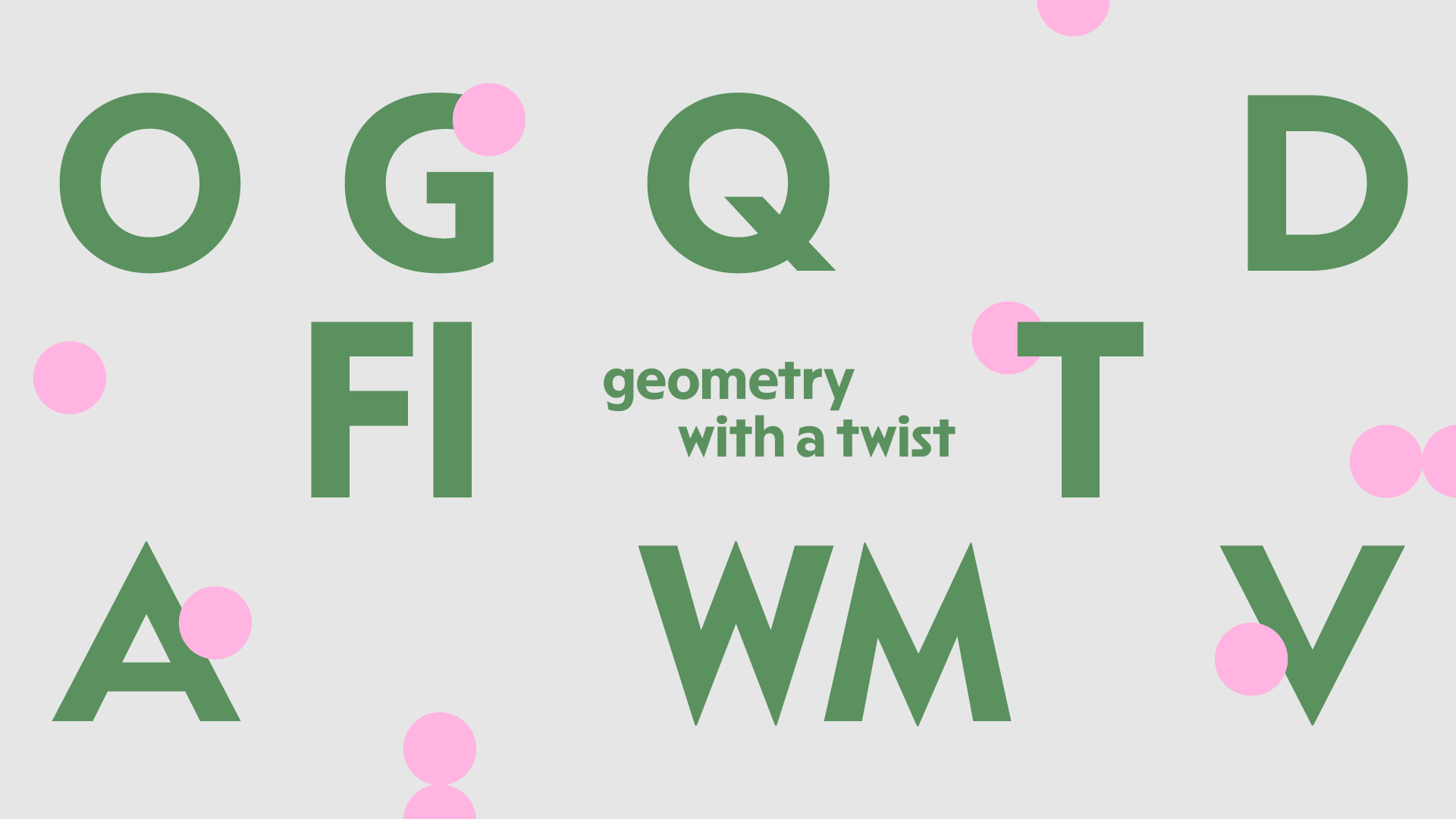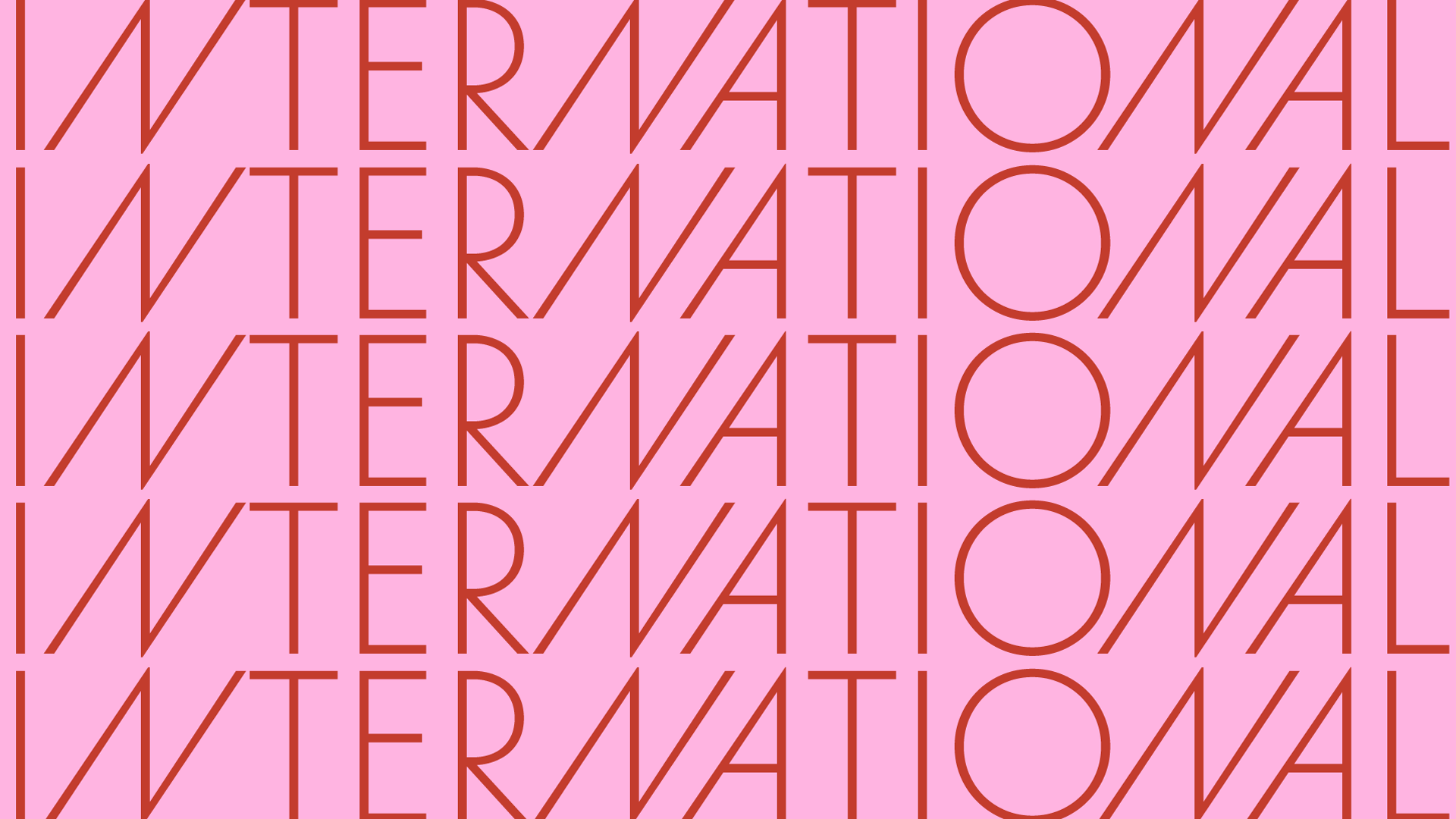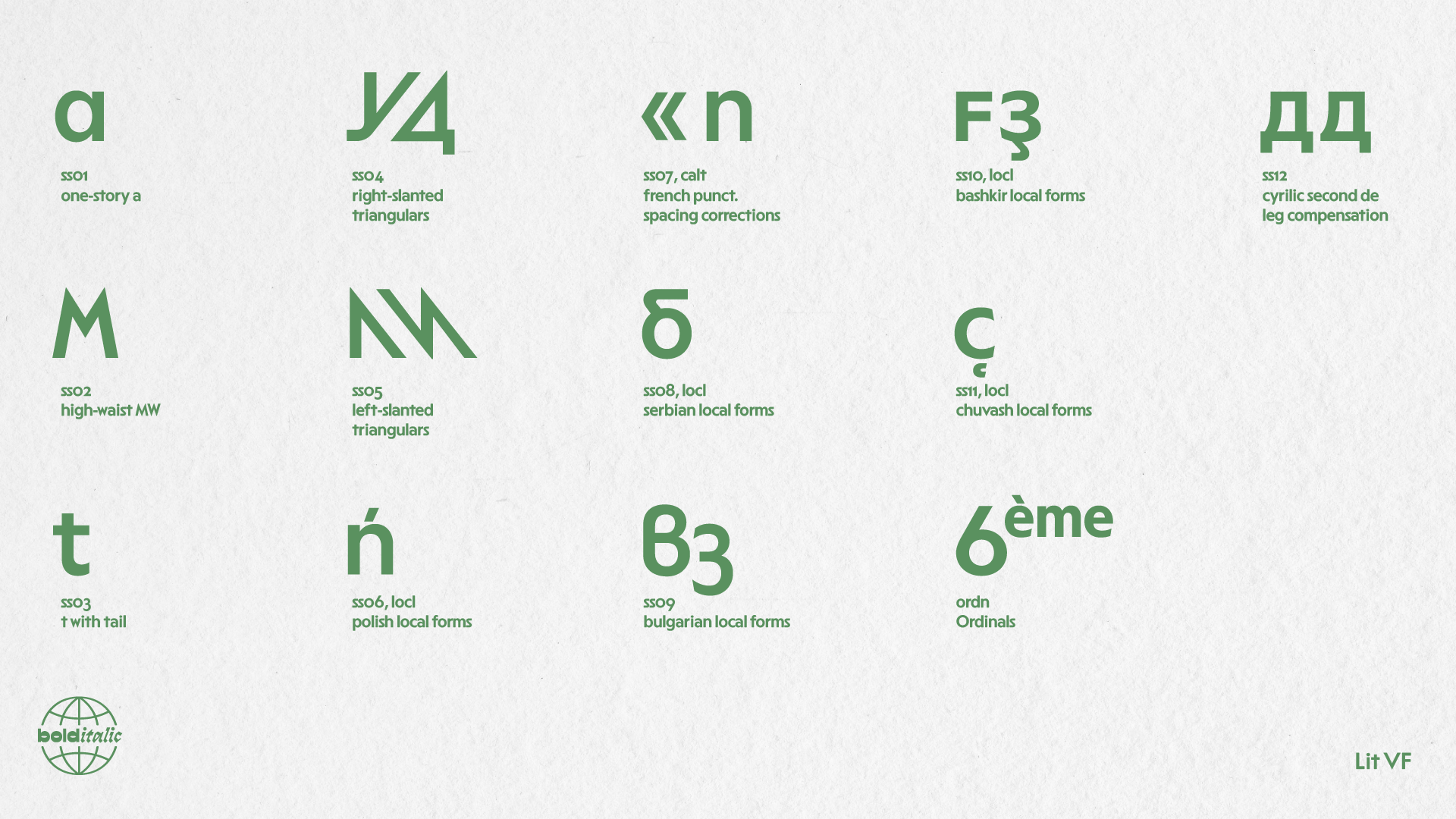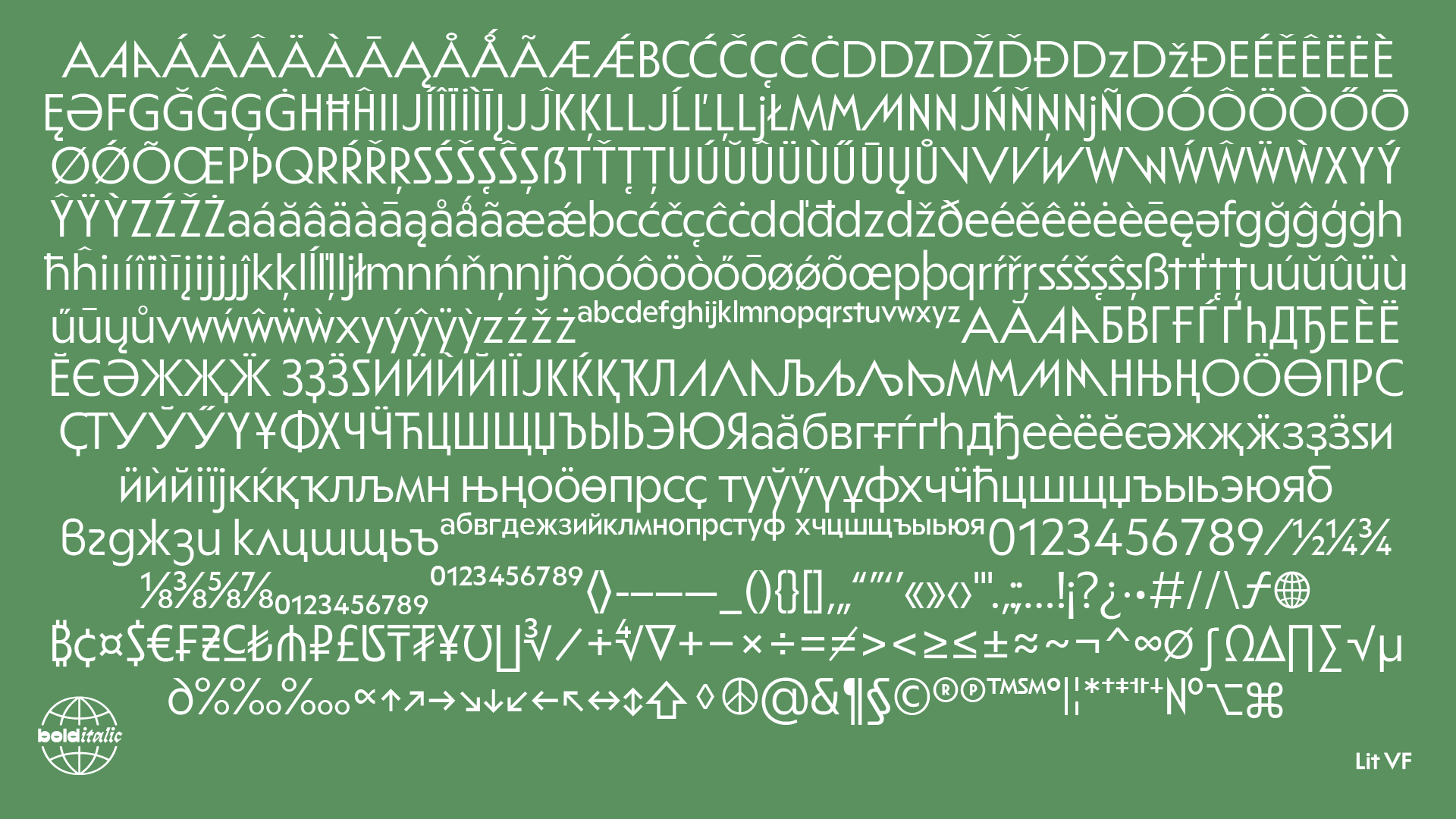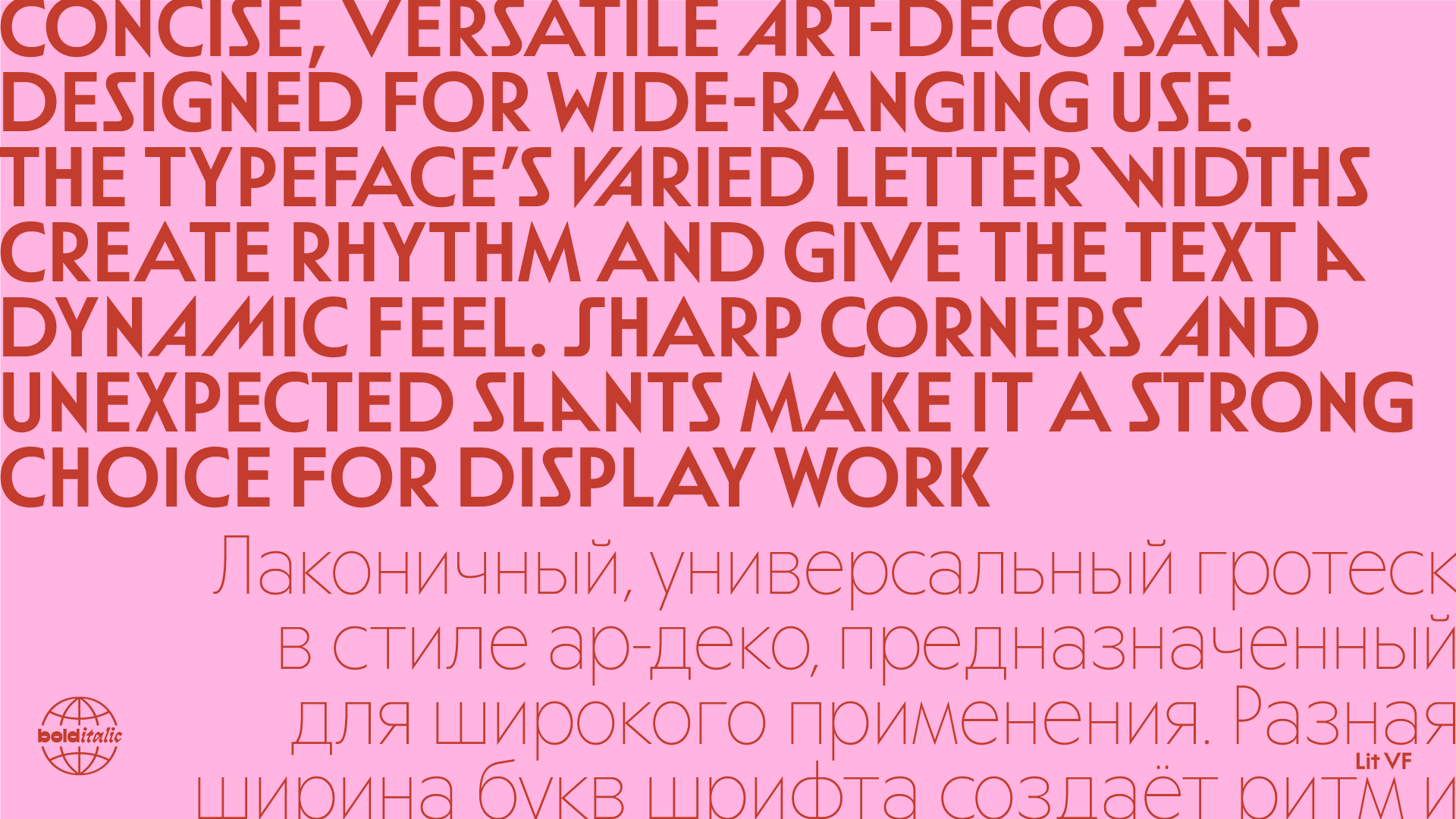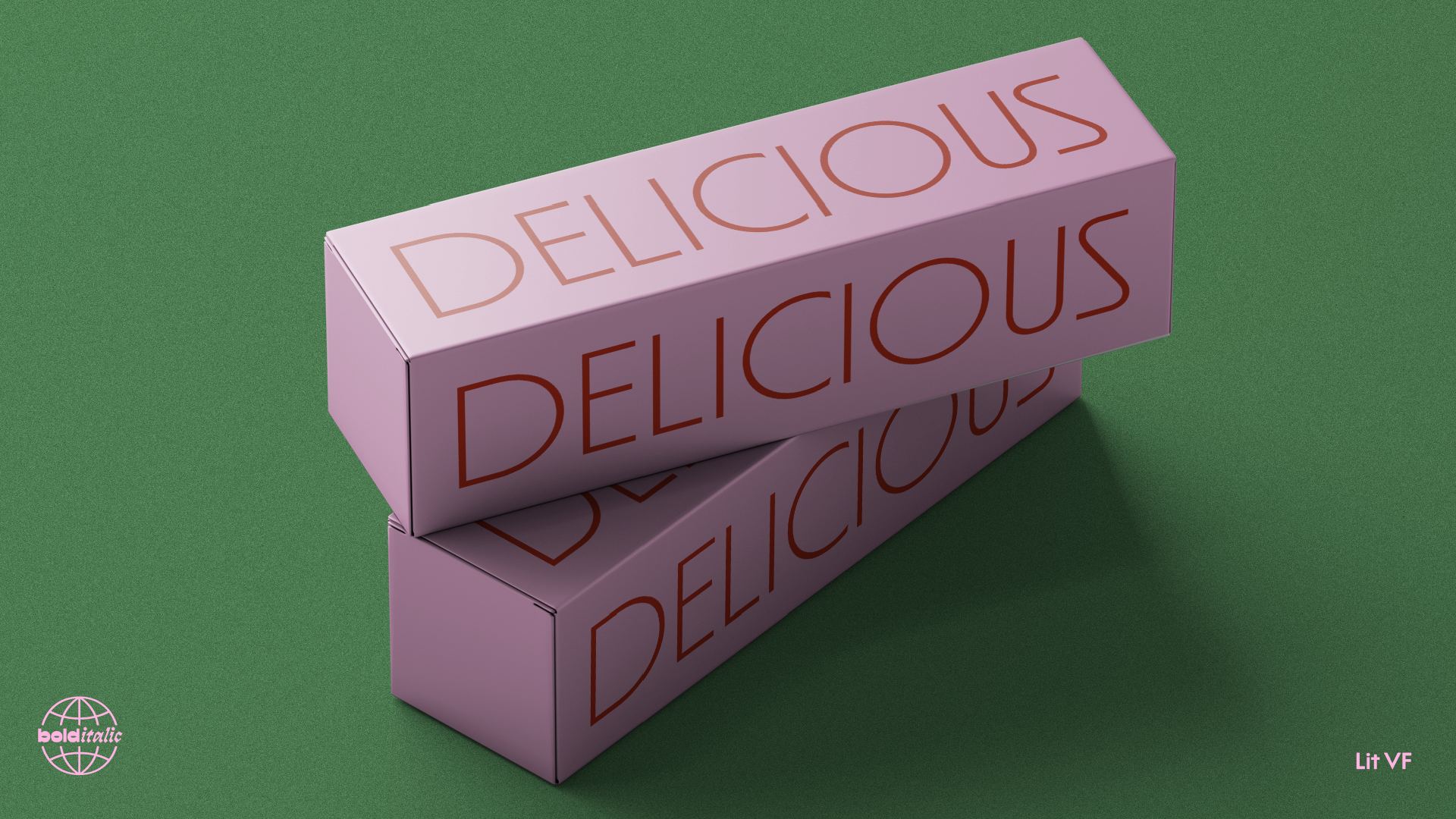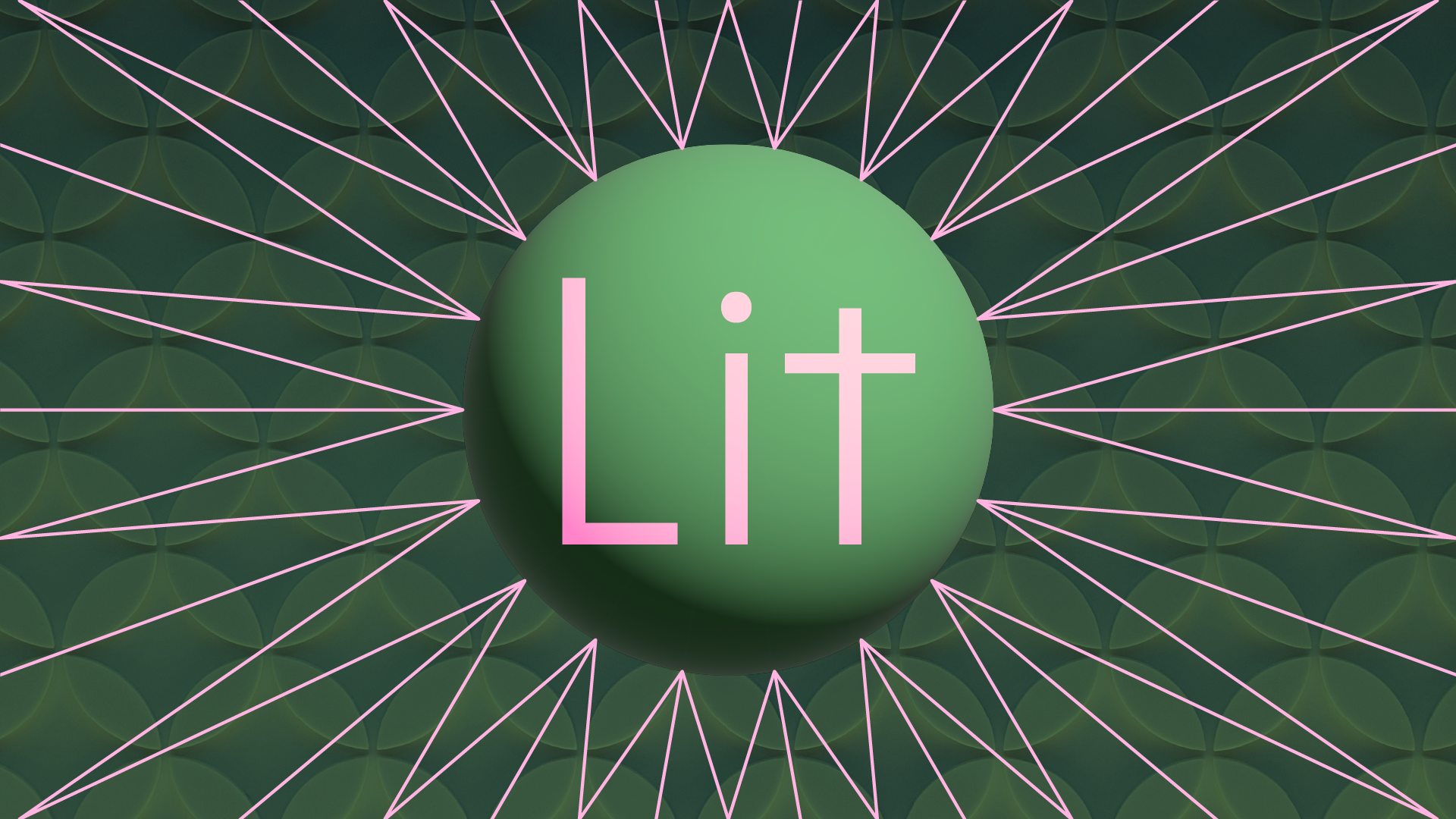
Lit
Лаконичный, универсальный гротеск в стиле ар-деко, предназначенный для широкого применения. Разная ширина букв шрифта создаёт ритм и придаёт тексту динамичность. Острые углы и неожиданные наклоны делают его отличным выбором для оформления.
У шрифта есть довольно большой диапазон начертаний по насыщенности (+ вариативный формат) и внушительный знаковый состав: языки Западной Европы и народов России + много альтернатив.